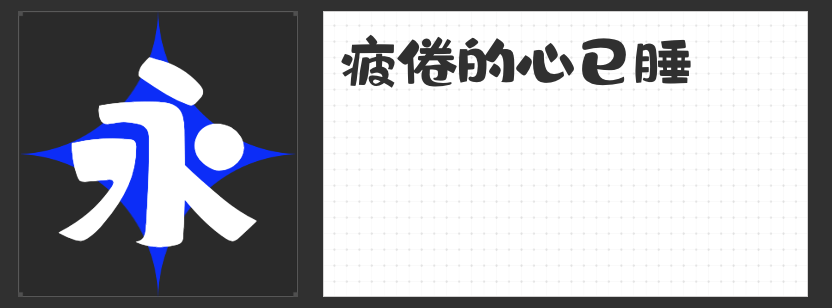
卡通感可爱字体推荐:让设计作品充满童趣与活力
在设计作品中融入卡通感的可爱字体,无疑能增添一份童趣与活力,让作品更加生动有趣。今天,我将为大家推荐四款充满卡通感的可爱字体,它们不仅各具特色,还能让你的设计作品瞬间脱颖而出。
一、字恋狂灵怪简
这款字体以其古灵精怪的特点而备受瞩目。笔画连带,折笔处处理为几何图形,别具一格。连笔流连贯穿,使得笔画更加流畅恣意,给人一种自由不羁的感觉。无论是用于标题还是正文,都能让作品充满个性和活力。
二、励字小星星简
励字小星星简样式俏皮可爱,充满了童稚的趣味。这款字体具有现代审美装饰趣味的书写风格,能够唤醒你对最初童心的向往。字体添加“小星星”作为装饰,字字都能给你惊喜。拙朴的线条和辨识性强的字体特点,使其广泛适用于二次元及三次元的视觉语境。无论是海报设计还是包装设计,都能轻松驾驭。
三、字圈也字多肉体
这款字体字型圆润饱满,Q弹可爱,给人一种和善可亲的感觉。它将转折写成流动感的圆弧形状,形成一个封闭的圆环,妙趣横生。比如“田”字,看起来就像出现在动画片中四格的圆形小窗,让人感受到快乐童真的氛围。这样的设计不仅增加了字体的趣味性,还能让作品更加亲切和融入感。
四、励字憨憨简
励字憨憨简以其呆萌的特点而备受欢迎。多用圆弧形笔画,充满活力,字形圆润饱满,显得活泼可爱。这款字体装饰性极强,无论是用于标题设计还是正文排版,都能让作品充满趣味性和视觉冲击力。
这四款卡通感可爱字体各有千秋,它们不仅能够满足你对于设计作品风格的需求,还能让你的作品在众多竞争者中脱颖而出。不妨尝试一下这些字体,为你的设计作品增添一份独特的魅力和童趣吧!